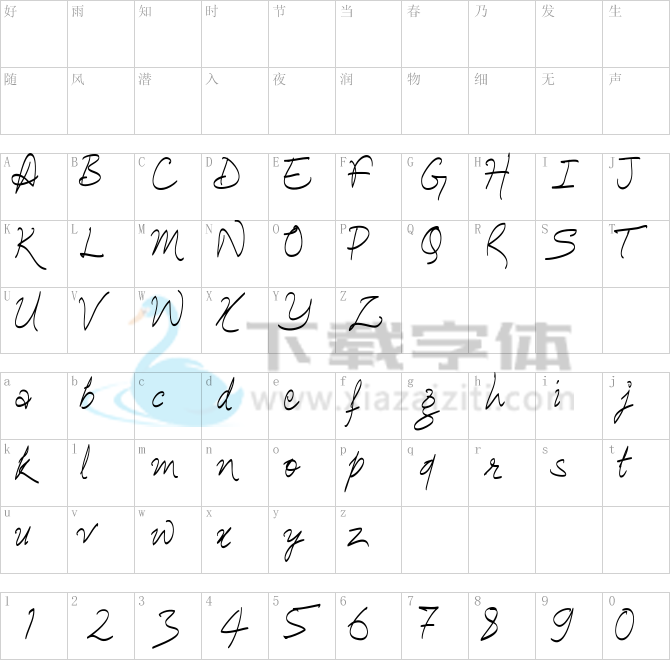
Ananda Hastakchyar.ttf字体下载
Ananda Hastakchyar.ttf字体下载,这款字体结构工整、笔画清晰,兼顾美观与易读性,适用于标题、正文、海报、包装、LOGO 等多种场景。字形优雅稳定,风格百搭耐看,适配日常排版与创意设计,让文字呈现更舒适、更具质感。Ananda Hastakchyar.ttf字体下载一笔一画,皆是细节,以均衡的比例、流畅的线条打造舒适视觉体验,字形端正大气,风格简约现代。无论是商业设计、品牌宣传还是日常排版,都能轻松驾驭,让文字更有格调与力量。Ananda Hastakchyar.ttf字体下载字体下载。